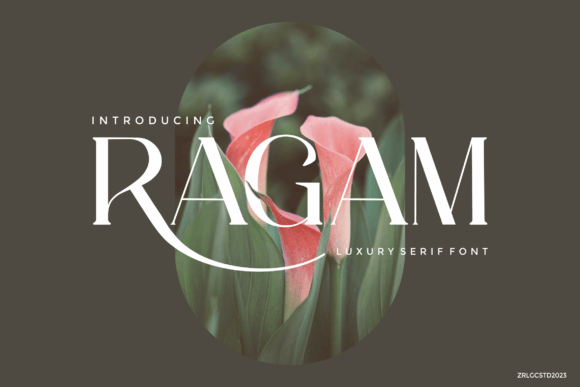
Ragam Luxury
Пошук відповідних елементів дизайну може бути складним, але Ragam Luxury пропонує виняткову колекцію, яка миттєво покращить вашу роботу.
Незалежно від того, чи створюєте ви продукти POD (друк на вимогу), весільні запрошення або графіку для соціальних мереж, Ragam Luxury стане ідеальним вибором.